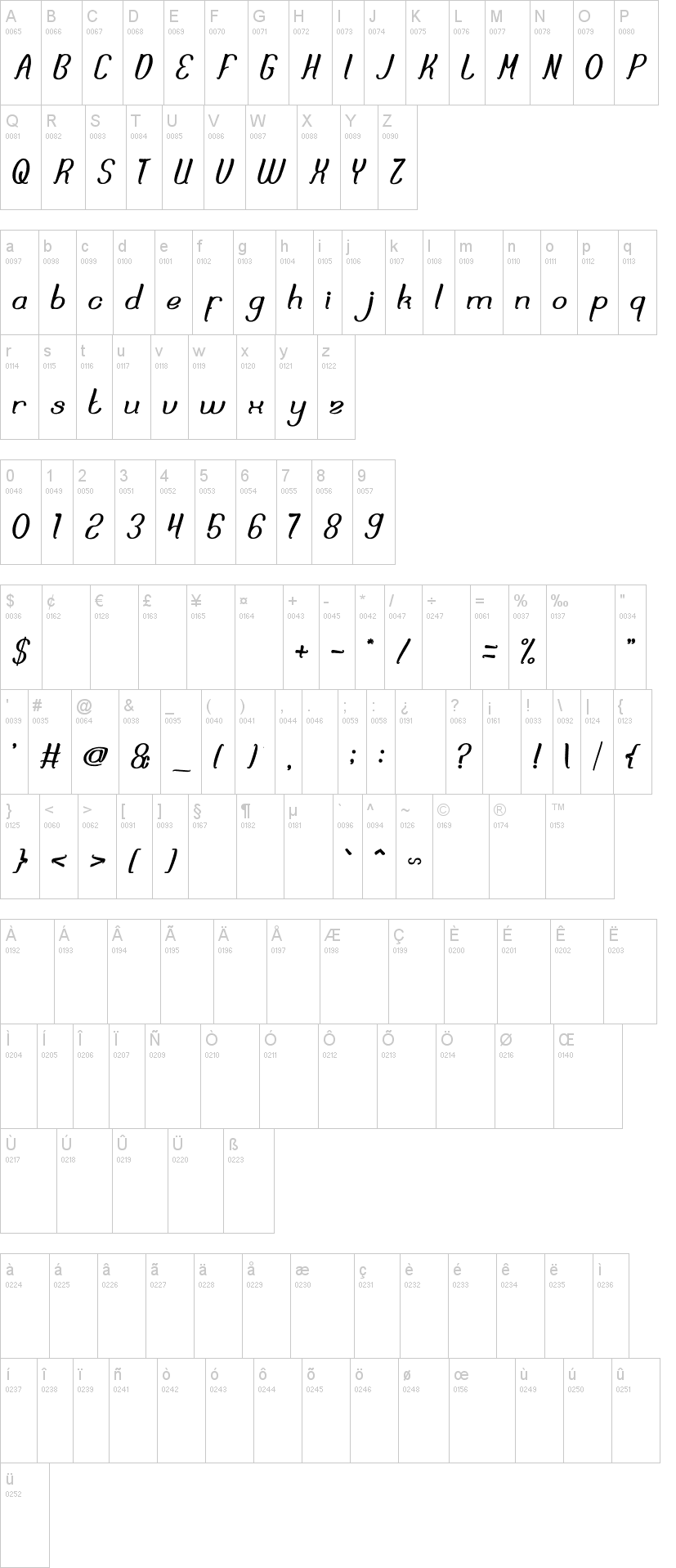
Dream Reality
Dream Reality 是一种现代化的字体,它具有一种清晰和简洁的外观,同时也充满了一些艺术品的感觉。这种字体的字母形状非常流畅,每个字母都有一些微妙的曲线,使得它们看起来很柔和。Dream Reality 字体可以在各种设计项目中使用,例如标志、海报、名片、宣传册和网站设计等。它的设计灵感来自于现代艺术和设计趋势,使得它非常适用于富有创意性的项目。同时,该字体也非常易于阅读,因此它可以用于文本和标题。总之,Dream Reality 字体是一种现代化、具有艺术感和易于阅读的字体,适用于各种设计项目。
Dream Reality是一款非常不错的手写艺术字体,具有很好的视觉感,适合于文化类的宣传设计、商业类品牌的广告和产品包装设计以及个性化文字排版等较多场景。
Dream Reality字符映射图